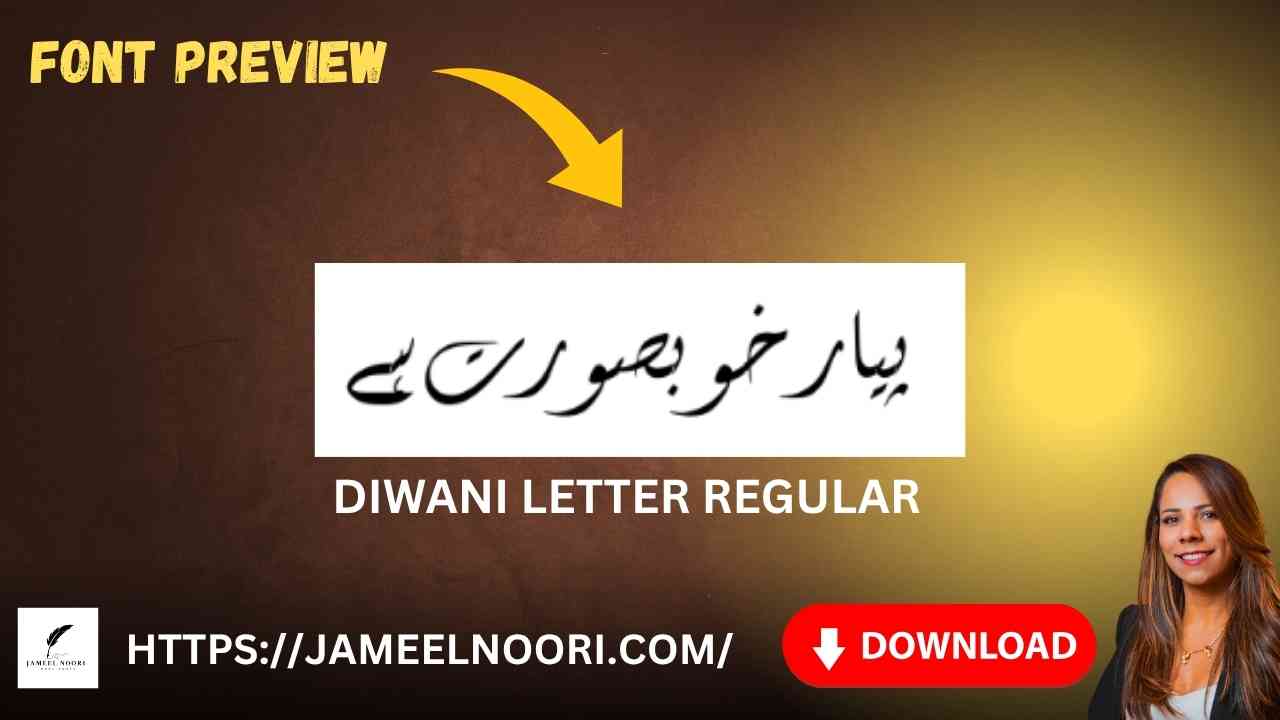
Agar aap Urdu design, calligraphy ya official typing ke liye stylish aur elegant font dhoond rahe hain, to Download Urdu font Diwani Letter Regular aap ke liye best choice ho sakta hai. Yeh font apni Arabic touch aur royal feel ki wajah se widely use hota hai, khaaskar Pakistan ke designers aur Urdu bloggers ke darmiyan.
What is Diwani Letter Regular Font?
Download Urdu font Diwani Letter Regular aik popular TrueType Urdu font hai jo Arabic aur Nastaliq styles ko merge karta hai. Is font ka design bohot khubsurat aur artistic hai, jo headings, logos, aur documents mein Urdu ka asar aur elegance add karta hai.
Key Features:
- Stylish Diwani Arabic Script
- Perfect for Urdu titles & headers
Why Use Diwani Letter Regular Font in Pakistan?
Pakistan mein Download Urdu font Diwani Letter Regular ko kai purposes ke liye use kiya jata hai, jaise:
- Urdu calligraphy designs
- Islamic invitation cards
- Urdu poetry blogs
- Educational material headings
Is font ka unique Diwani style aapke Urdu content ko visually appealing banata hai.
Final Verdict – Is Diwani Letter Regular Worth It?
Agar aapko ek stylish aur classic Urdu font chahiye jo aapke documents ya graphics ko traditional yet elegant look de, to Download Urdu font Diwani Letter Regular best option hai. Is font ka artistic Diwani style har Urdu content ko standout banata hai — specially Pakistan ke users ke liye.
FAQs – Diwani Letter Regular Font
What is Diwani Letter Regular font used for?
It is mainly used for Urdu calligraphy, poetry, religious content, and official titles.